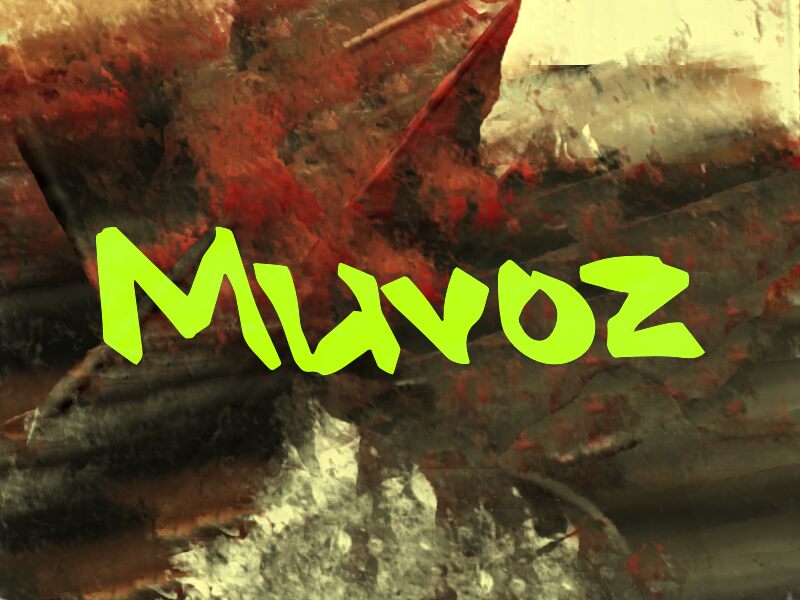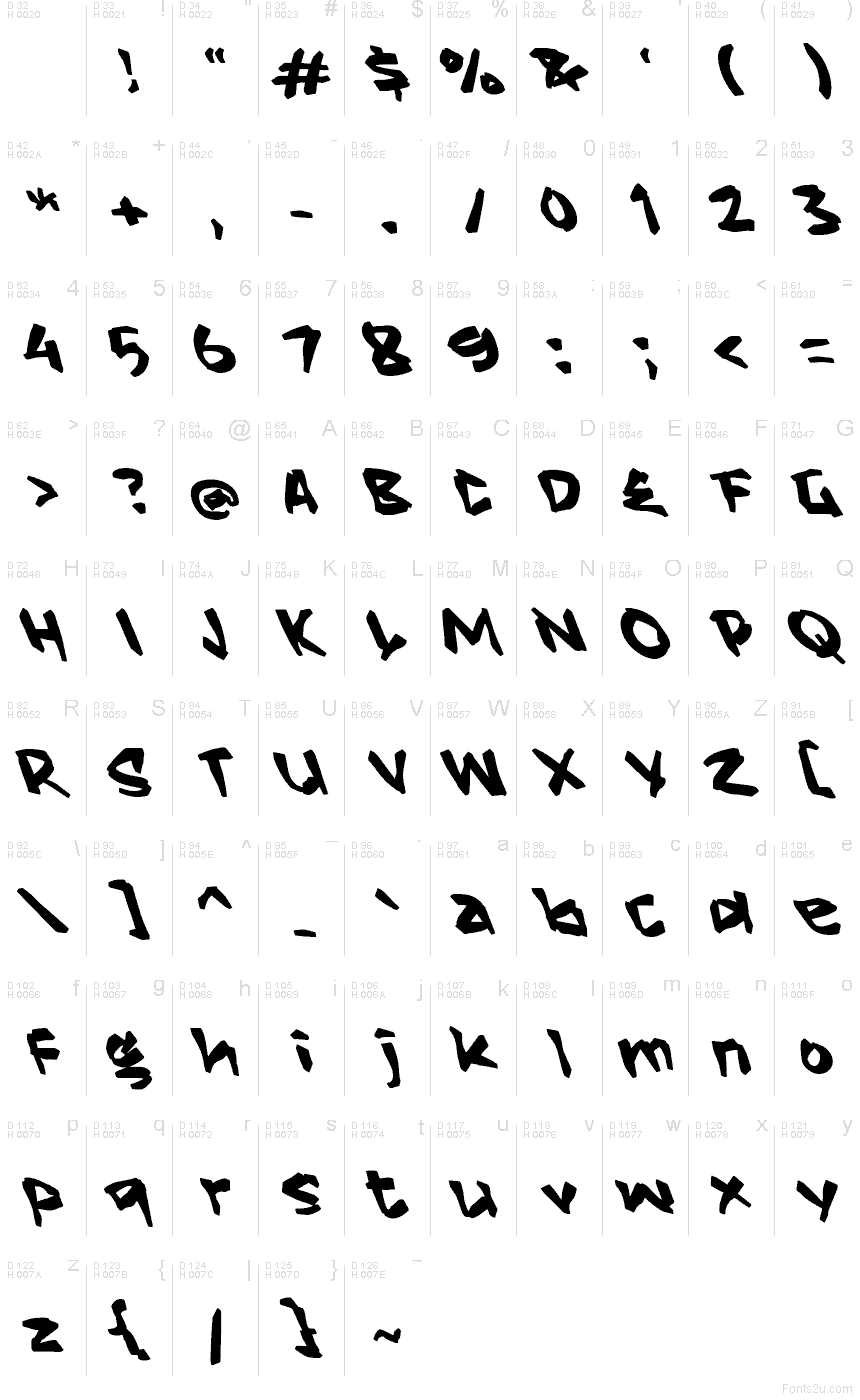
Muvoz
La police Muvoz créée par Wep est une police graffiti gratuite, dotée de formes de lettres anguleuses dessinées à la main et de coupes nettes et inclinées qui donnent au lettrage l'aspect d'un tag urbain. Les tracés conservent un rythme brut et irrégulier, avec des jointures pointues et des creux arrondis qui donnent l'impression que les lettres ont été tracées au marqueur rapide plutôt que construites à partir d'une géométrie rigide.
Muvoz est idéale pour le branding streetwear, les affiches de musique, les graphismes skate, les logos urbains et les flyers d'événements audacieux, car son contour brut capture l'énergie des murs de la ville sans fioritures inutiles. Cette police gratuite convient également aux pochettes d'albums, aux designs d'autocollants et aux titres promotionnels où l'on recherche une esthétique graffiti directe et manuscrite.